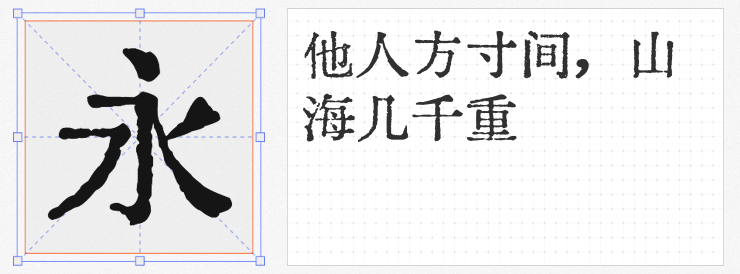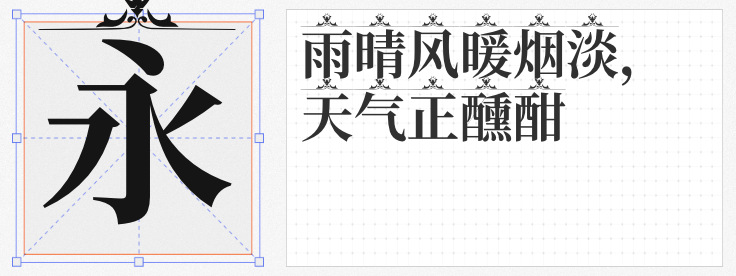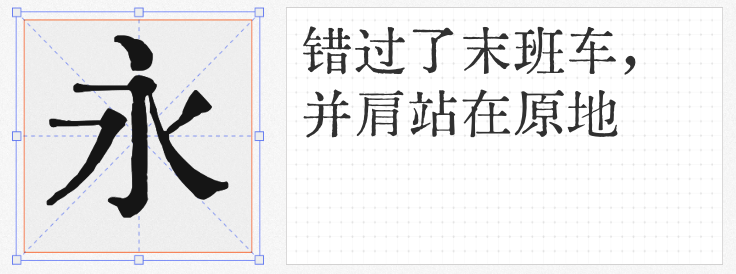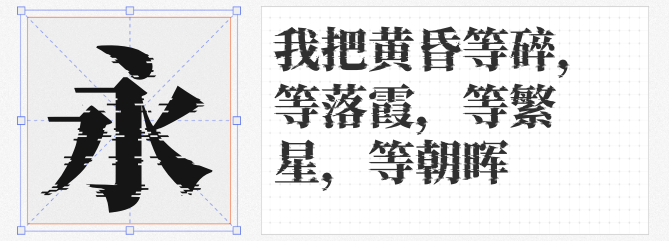
在平面设计的世界里,字体不仅是文字的载体,更是视觉表达的灵魂。今天为大家精选四款风格独特的免费商用字体,它们以颠覆传统的创意设计,为作品注入令人过目难忘的视觉张力。
1. 纳米老宋
这款基于汇文明朝体改良的字体,通过遍玨体的复合修改,在传统宋体骨架上注入未来科技感。笔画转折处采用金属切割般的锐利倒角,横竖笔画末端点缀着像素化装饰,仿佛从数字世界穿越而来的古老文字。特别适合科技类海报、游戏界面等需要融合传统与现代的设计场景。
2. 京华老宋体
复刻自1961年北京新华字模厂经典字稿,这款字体完整保留了桃形点、鹅头勾等标志性特征。相较于现代宋体,其笔画更显丰腴圆润,字面布局遵循黄金分割比例,既保留了六七十年代印刷品的复古韵味,又通过微调的笔形比例呈现出工整秀丽的现代气质。在书籍装帧、文化类海报设计中能瞬间营造年代感。
3. 猫啃网故障宋
以思源宋体为基底,通过算法批量生成故障特效,这款字体自带数字时代的叛逆基因。错位、噪点、色散等效果随机分布在笔画间,每个字符都呈现出独一无二的破损美感。虽然部分字形存在程序生成的瑕疵,但正是这种不完美构成了其独特的视觉语言,特别适合音乐节海报、潮牌设计等年轻化场景。
4. 思源宋体花样钻纹
在思源宋体粗体基础上,设计师为6763个常用汉字添加了精密的钻纹装饰。这些源自传统纹样的细节处理,既保持了文字的可读性,又赋予其珠宝般的奢华质感。英文符号同样经过精心设计,与中文形成视觉呼应。在奢侈品包装、高端活动视觉系统中能瞬间提升设计格调。